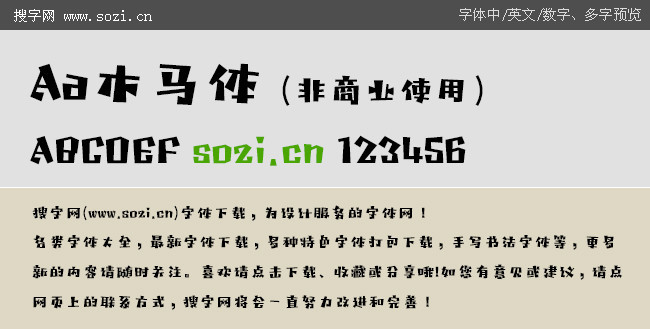
Aa木馬體
搜字網(wǎng)給大家提供一款A(yù)a木馬體(非商業(yè)使用)中文字體下載,該字體是一款中文藝術(shù)字體,以粗細(xì)兩種方頭筆畫制作,榫卯般的方頭筆畫好像木匠任意而為的奇異家具,寬大的中宮和自由的結(jié)構(gòu)都增強(qiáng)了有趣的卡通感,非常有意思,適合書裝設(shè)計(jì)、包裝、海報(bào)設(shè)計(jì)等應(yīng)用(此字體為個(gè)人非商用版,商用可以聯(lián)系QQ:1006760504)。